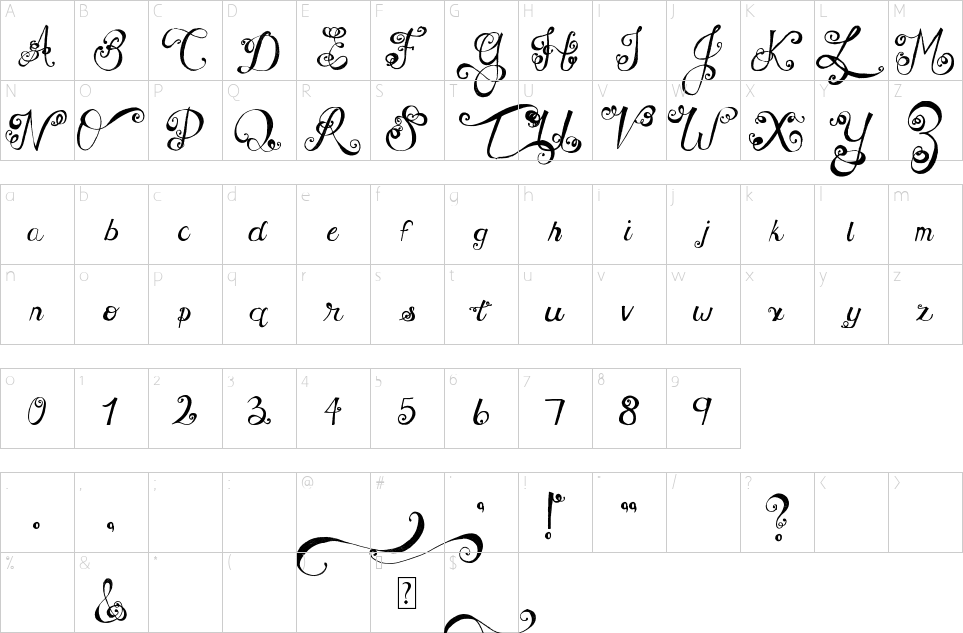
A MTF Under Your Skin é uma fonte gráfica elegante e sofisticada, projetada para criar um efeito inusitado em seus projetos. Inspirada no conceito de que nossa própria mente pode estar sempre em atividade, essa fonte oferece um visual único e moderno, adequado para uma variedade de ambientes de design. Desenvolvida pela Miss Tiina Fonts, ela tem sido uma opção popular para designers e criadores de conteúdo. Com seu estilo único, a MTF Under Your Skin pode transformar qualquer projeto em um verdadeiro destaque. Como parte do catálogo de fontes gratuitas da 1001 Free Fonts, ela está disponível para uso em projetos pessoais e comerciais. Se você está procurando uma fonte que traga um toque único e vibrante a seus trabalhos, a MTF Under Your Skin é uma ótima escolha.